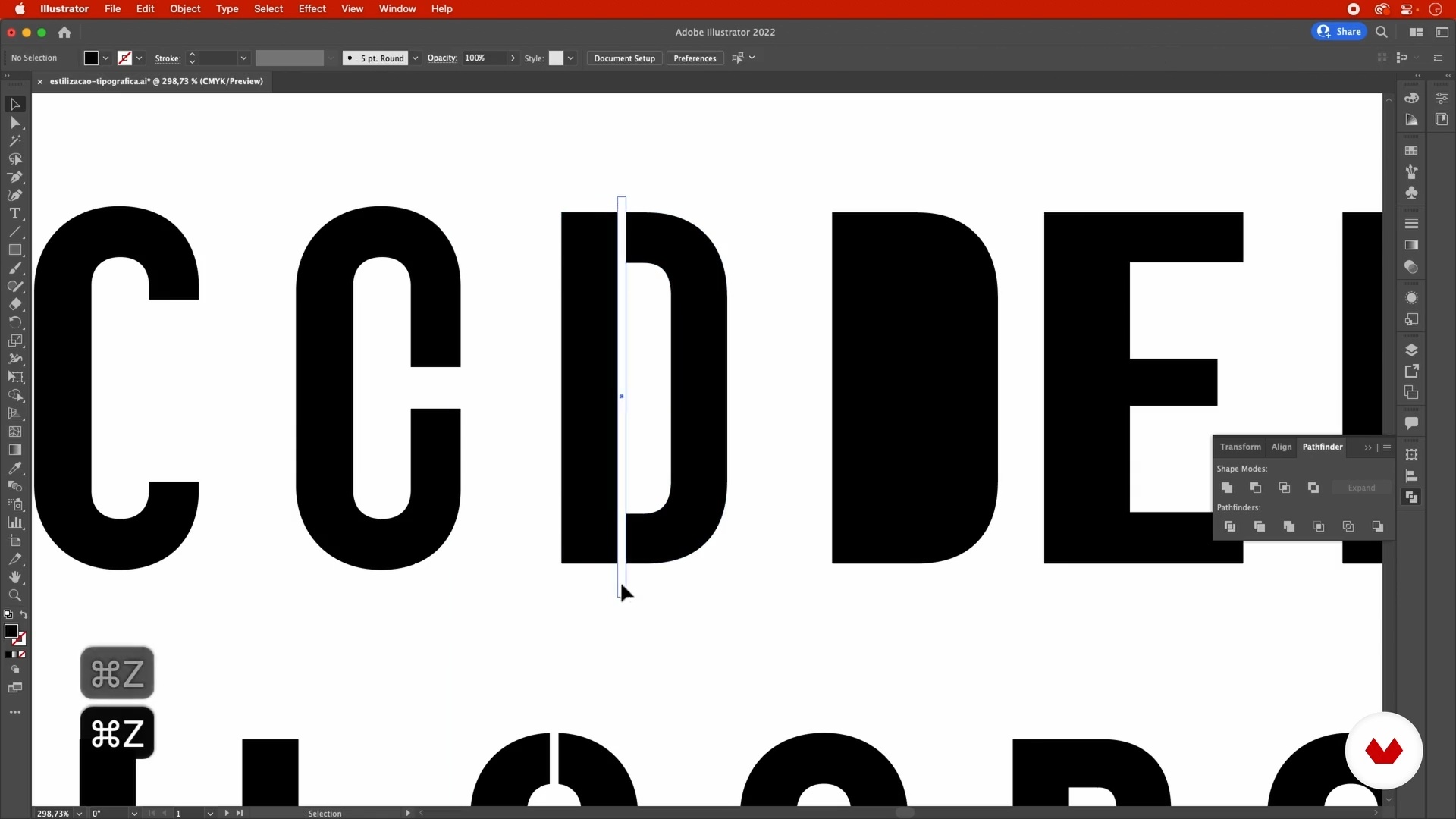
Manipulation typographique et style
À propos de la leçon : Manipulation typographique et style
“Maintenant, comprenons mieux la forme des lettres et leur anatomie afin de pouvoir jouer avec et l'utiliser à notre avantage pour faire passer des messages et raconter des histoires. ”
Dans cette leçon, Leandro Rodrigues aborde le sujet : Manipulation typographique et style, qui fait partie du cours Domestika en ligne : Typographie pour des projets numériques et imprimés. Apprenez à sélectionner, combiner et styliser des polices de caractères pour des titres, des sous-titres et des textes longs et à mettre en page vos publications.
“Manipulation typographique et style Dans cette leçon, nous en apprendrons plus sur la forme des lettres pour pouvoir l'utiliser à notre avantage lorsqu'il s'agit de raconter des histoires et de faire passer un message. Allez? Nous devons nous arrêter un peu plus longtemps au sujet de l'anatomie et de la forme des lettres. Par exemple, dans ces diagrammes les plus élémentaires, on voit, en partant d'ici à gauche, en haut, que la partie principale d'une lettre verticale c'est la tige. Plus à côté, on voit que la partie arrondie d'un A minuscule s'appelle le renflement. Nous savons déjà ce qu'...”